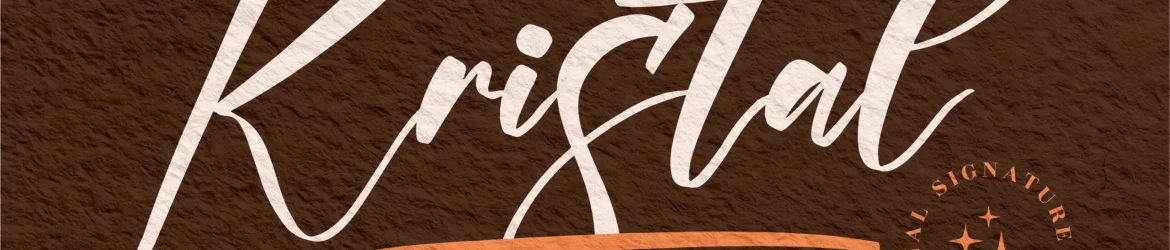
A Kristal Font é uma moderna assinatura feita à mão, criada pelo estúdio Perspectype Studio. Seu design elegante faz dele uma escolha perfeita para qualquer projeto de gráfica que exija um toque de sofisticação premium. Com seu estilo fluido e fácil de ler, a Kristal Font é perfeitamente adaptável aos seus melhores projetos, incluindo logomarcas, design de marca, designs de mobiliário, embalagens de produtos, tigelas, frases, posters, sacolas de shopping, camisetas, capas de livros, cartões de nome, convites de casamento e cartões de visita. Seja o momento da sua próxima ação, seja para imprimir ou para digitalizar em um aplicativo, essa fonte moderna é perfeita para aqueles momentos especiais que você quer manter marcados com uma assinatura única e elegante.